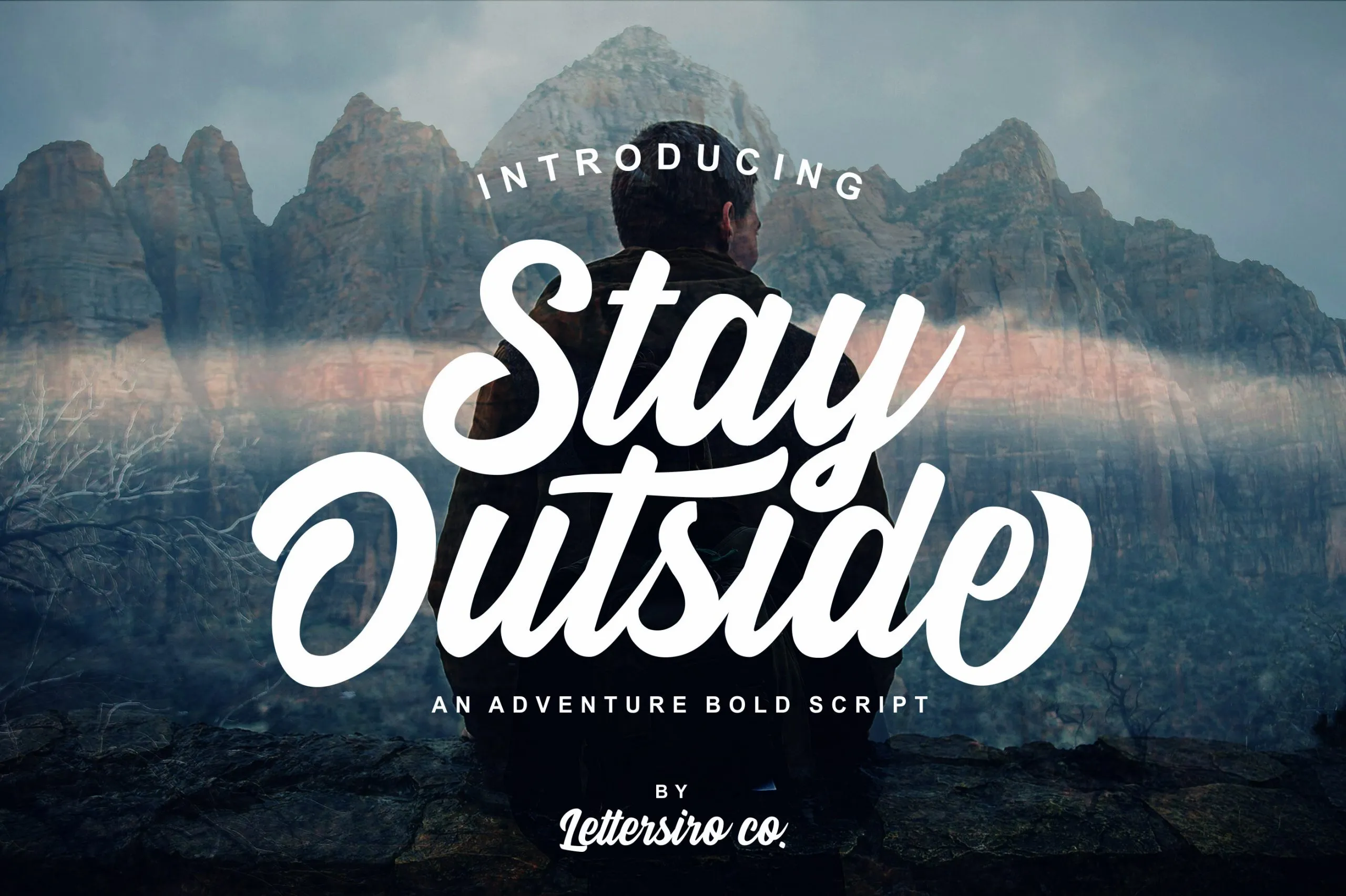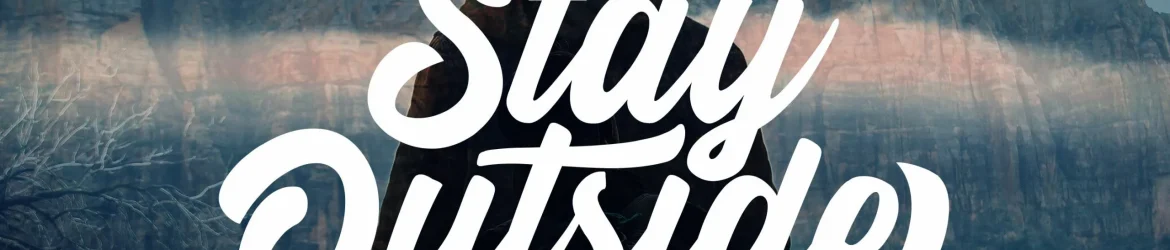
Através da Lettersiro Co., apresentamos Stay Outside, uma fonte script premium que combina elementos modernos e dinâmicos com um toque fluido e elegante. Esta fonte traz à vida sua inspiração natural, oferecendo toneladas de gílios incrivelmente detalhados, incluindo swashes suaves e vibrantes. Stay Outside é perfeita para projetos variados, seja você criando uma arte minimalista ou artesanato mais elaborado. Seu design fluido e moderno permite quebrar o padrão convencional e trazer vida à sua arte digitizada. Ideal para criações de arte digital, ilustrações, logotipos e até mesmo letras de música. A Lettersiro Co. investiu tempo em criar Stay Outside, resultando num produto excepcionalmente sofisticado que se destacará nos seus trabalhos. Esta fonte está disponível gratuitamente hoje no Creative Fabrica. Composta por toneladas de detalhes vibrantes e fluidos, Stay Outside é uma escolha inteligente para qualquer designer ou artista criativo em busca de um produto premium e inspirador.